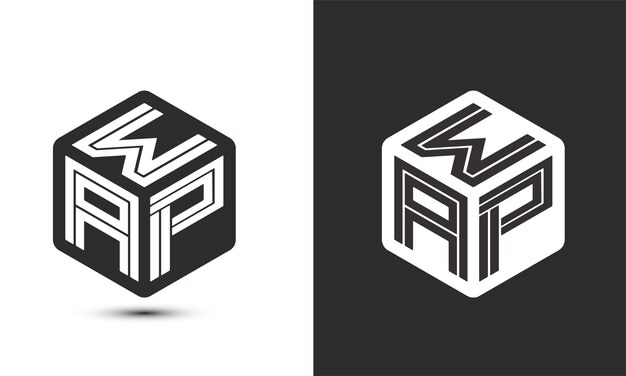
WPP letter logo design with illustrator cube logo wektor logo modern alphabet font overlap style
Projekt logo litery w p z ilustratorem logotyp sześcienny logotyp wektorowy nowoczesny alfabet czcionka nakładający się styl ikona logo Premium Business biały kolor na czarnym tle